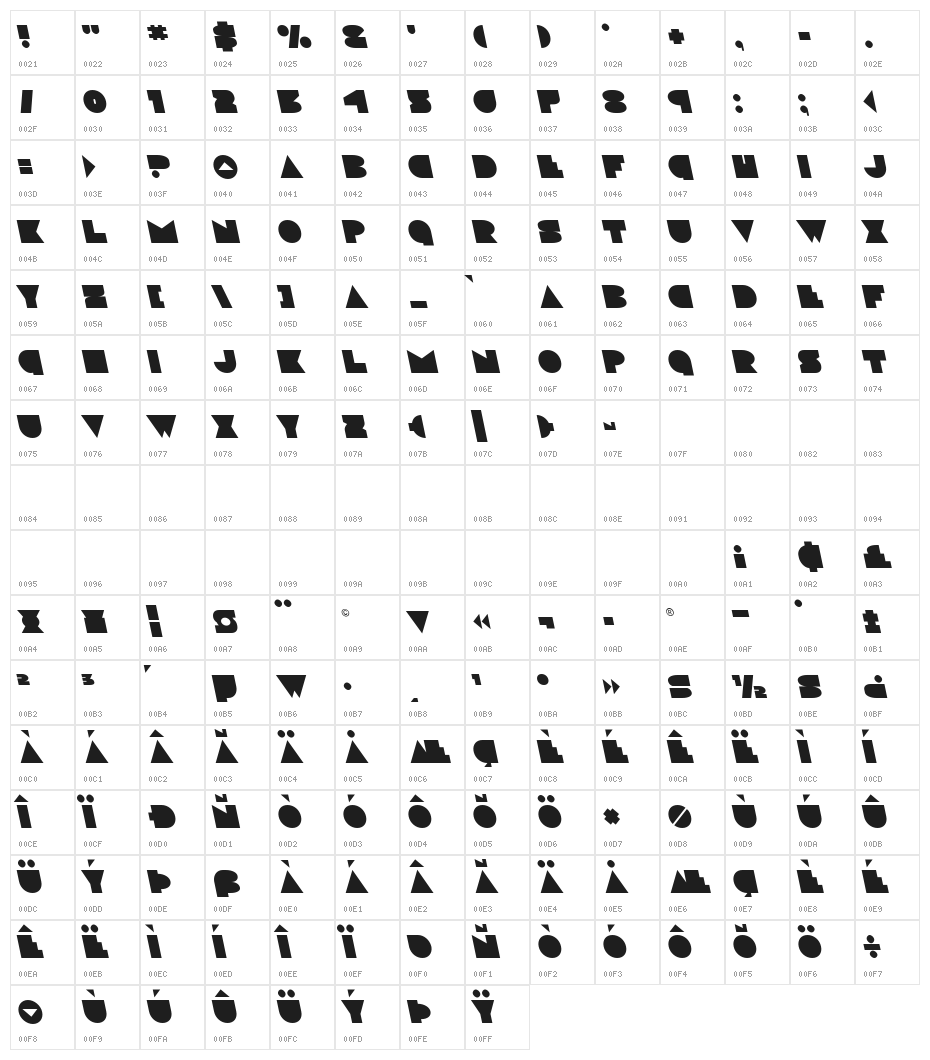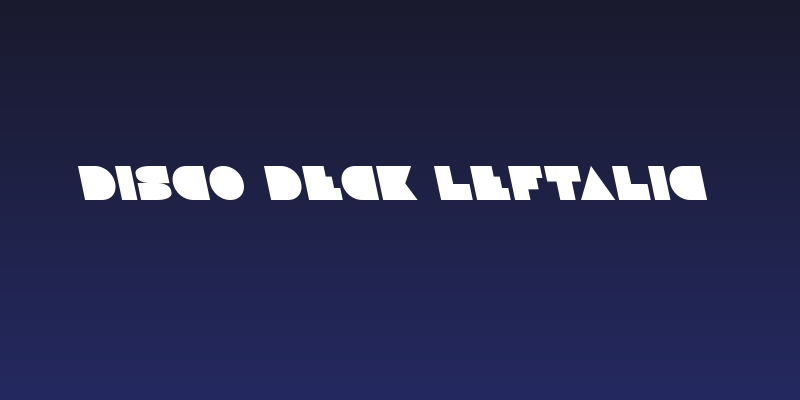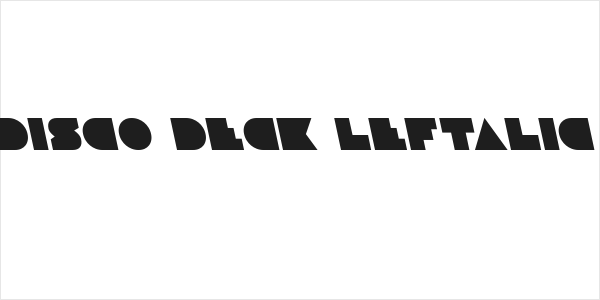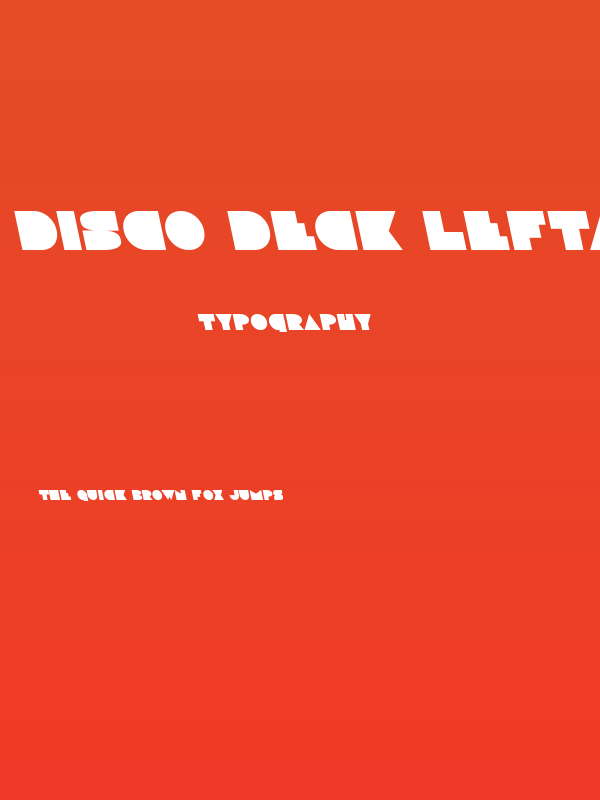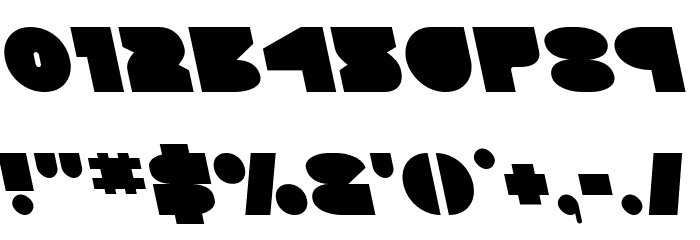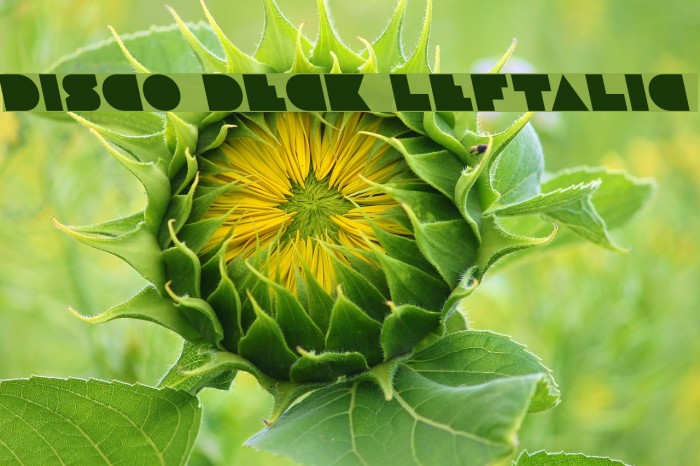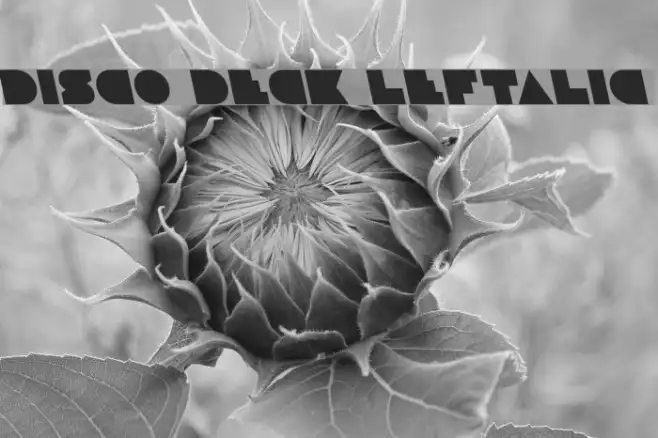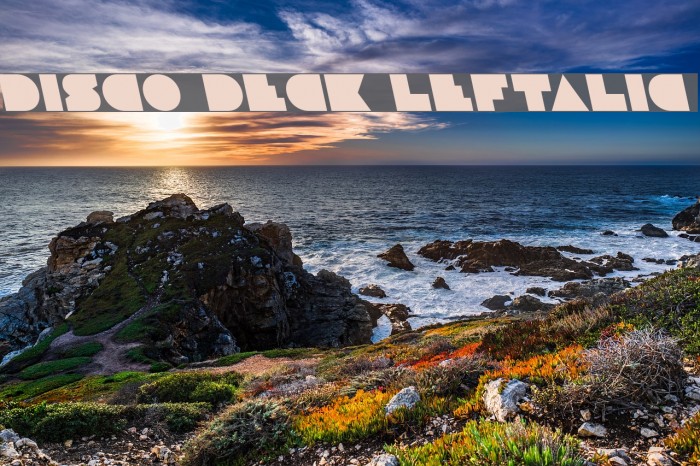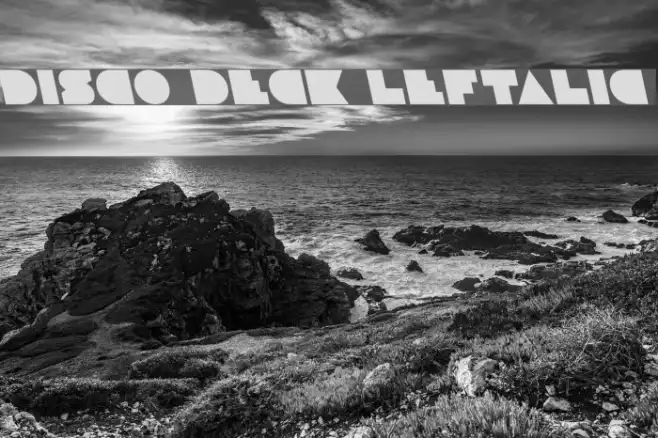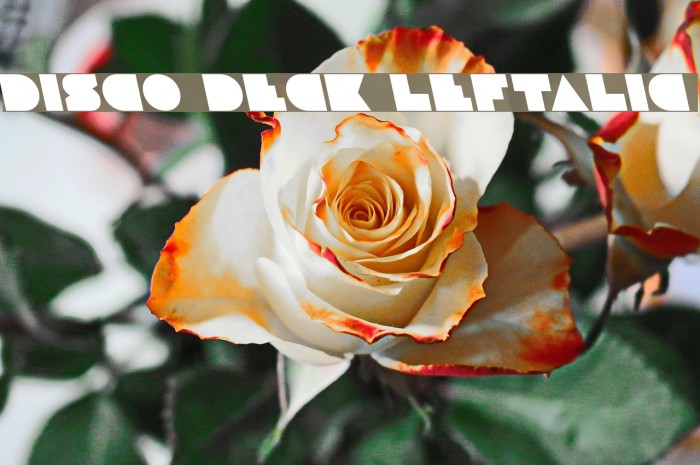
Disco Deck Leftalic Font
| Proyectos propuestos | Ideal for posters, album covers, event flyers, and branding that seeks a bold and modern aesthetic. |